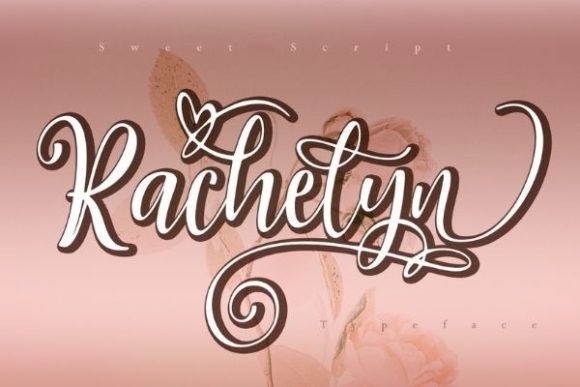
Rachelyn
قد يكون العثور على عناصر التصميم المناسبة أمرًا صعبًا، ولكن Rachelyn يقدم مجموعة استثنائية ترتقي بعملك على الفور.
سواء كنت تقوم بإنشاء منتجات الطباعة عند الطلب أو دعوات الزفاف أو رسومات وسائل التواصل الاجتماعي، فإن Rachelyn هو الخيار المثالي.